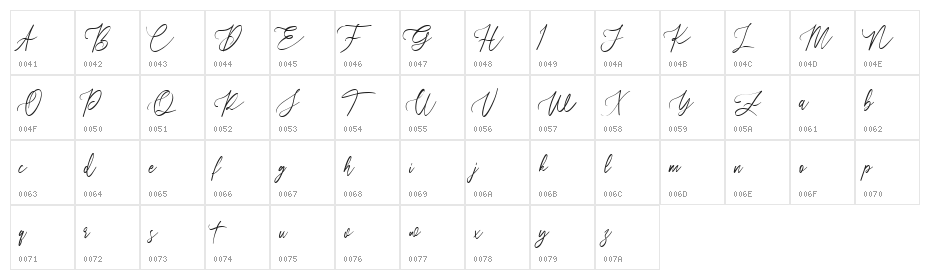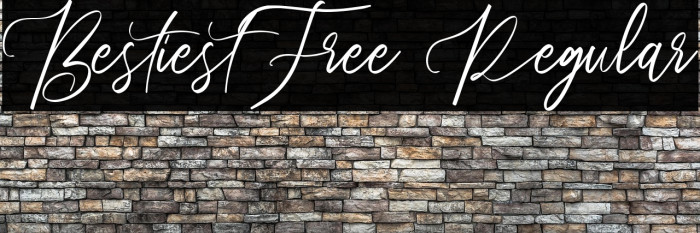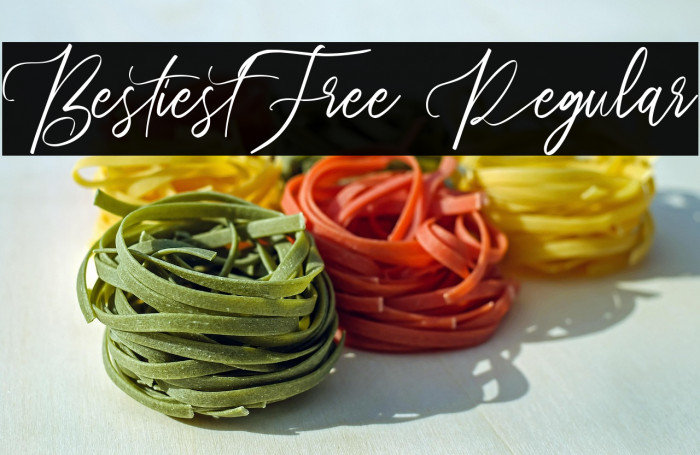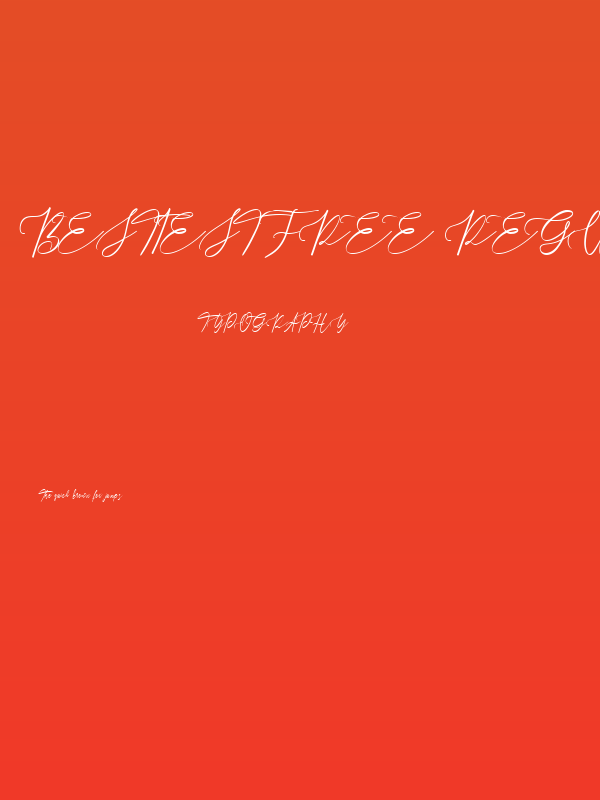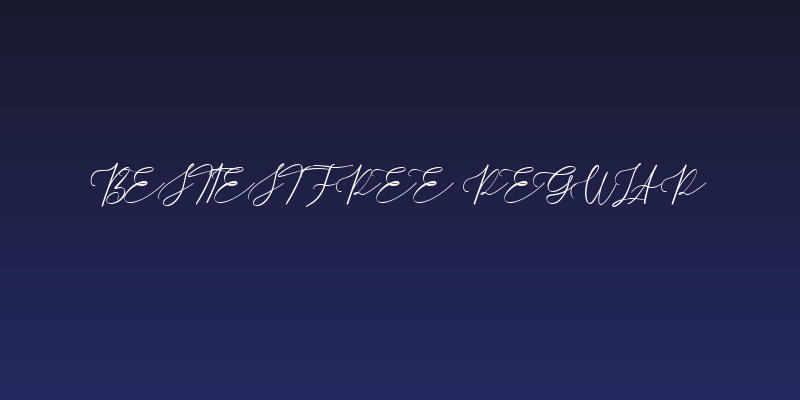
Bestiest Free Regular Font
| Stile generale | Elegant, Handwritten |
| Caso d'uso | Logos, Invitations, Personal Branding |
| Progetti proposti | Ideal for wedding invitations, greeting cards, personal branding, and elegant logos. |